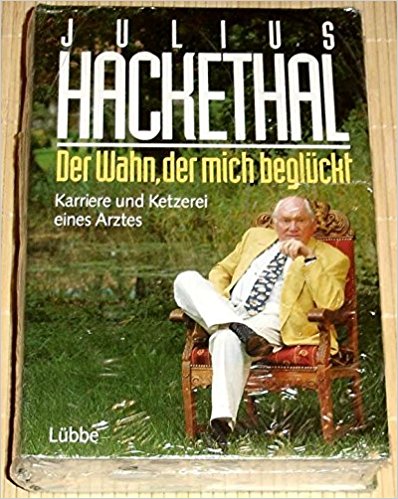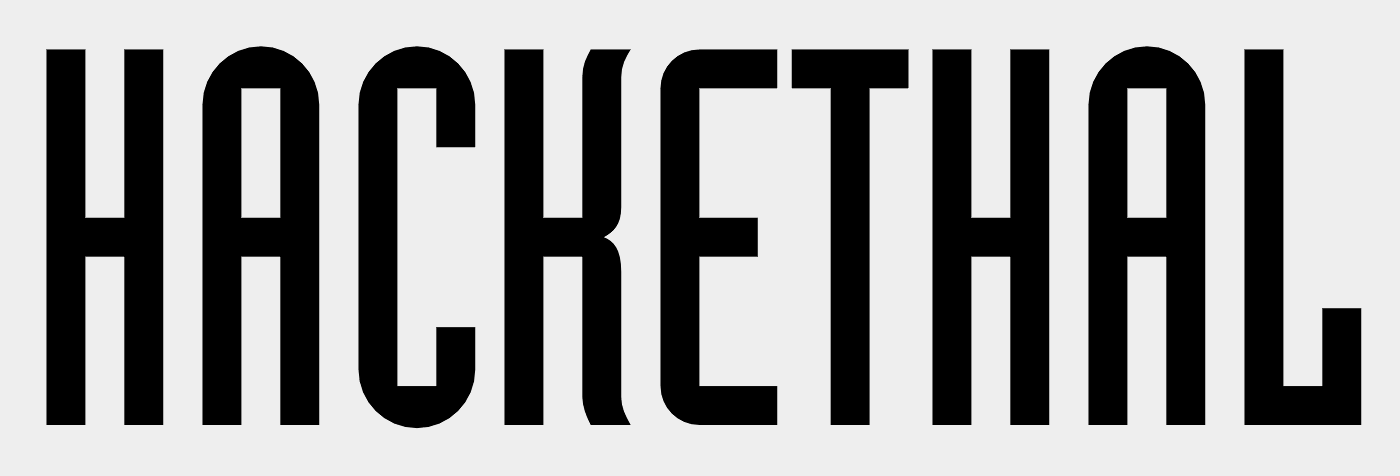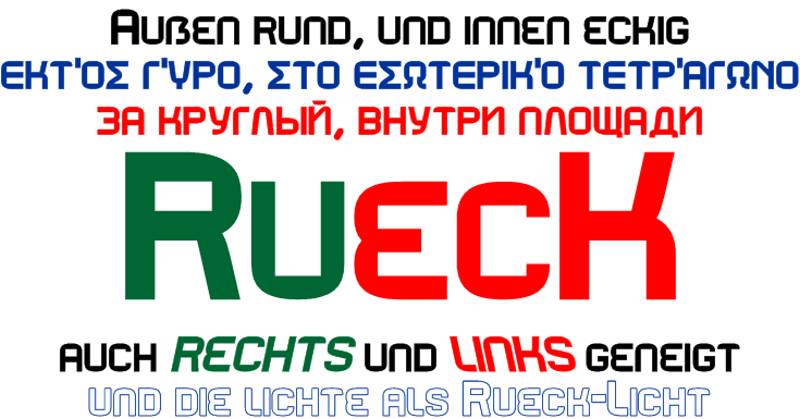
Eigentlich keine Schriftensuche
Vor längerer Zeit gab es hier mal eine Frage, ob es eine Schrift gibt die außen herum abgerundete Formen hat, deren Punzen aber eckig sind. Da gab es, so meine ich mich zu erinnern kein richtiges Ergebnis, zumal auch kein Beispiel so einer Schrift gezeigt wurde.
Ich hatte, angeregt von dieser Frage ja damals diese Schrift gezeichnet:
Heute spreche ich mit einem Freund, und er erzählt mir über seine Gedanken betreffend einer Nierenstein-OP. Irgendwie kamen wir so kurz auf Dr. Julius Hackethal zu sprechen. Wir sprachen längst über andere Themen, als er mir plötzlich erzählte, dass sein Psychotherapeut (Wegen Klaustrophobie)  auf den Namen Dr. Wahn hört, und fragte, ob er dem wohl ein Buch schenken solle, dann schickte er mir den Link hierzu:
Jetzt guck ich doch ein wenig dumm aus der Wäsche. Aber vielleicht weiß da jemand mehr...
Toll. Warum haben wir das damals nicht gefunden? OK, ich hätte dann was weniger.